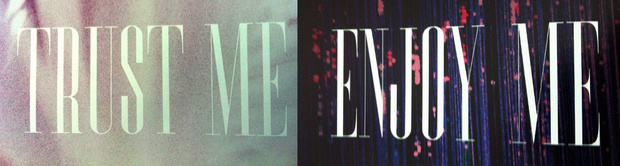
Bodoni in noch compressed-ter
Vielleicht die Long Tall Sally, deren R bearbeitet wurde?
Die Richtung ist gut, aber ich glaube nicht, daß hier die Raffinesse besessen wurde die Buchstaben noch zu verändern. Generell scheint sie aber noch mehr Kontrast zu haben und noch compresster zu sein...
Ich bin mir fast sicher, dass wir diesen oder einen seht ähnlichen Font hier schon mal gesucht hatten … müsstest mal in Ruhe suchen.